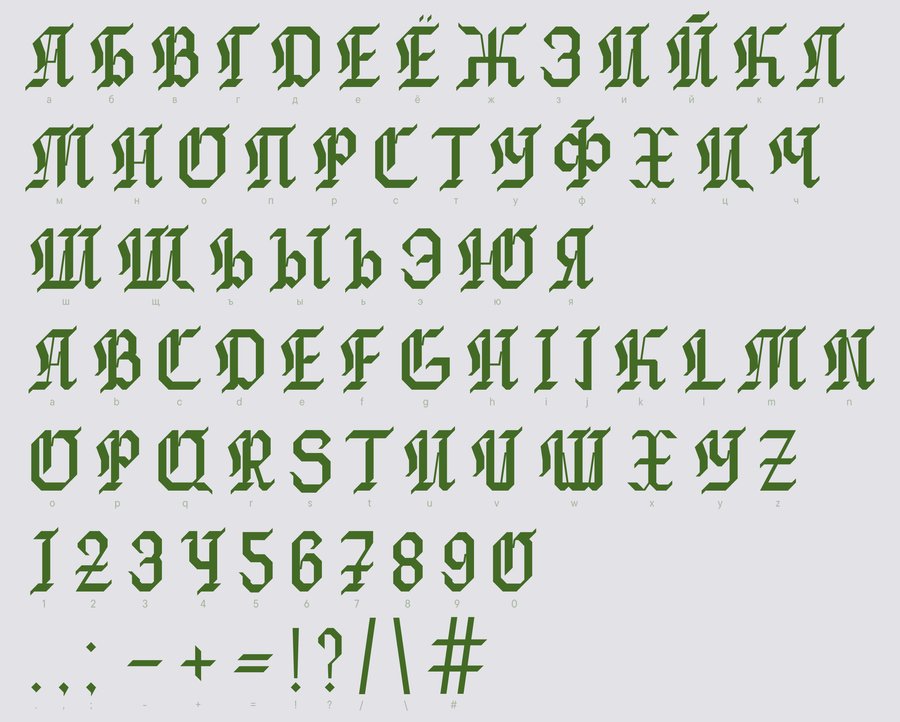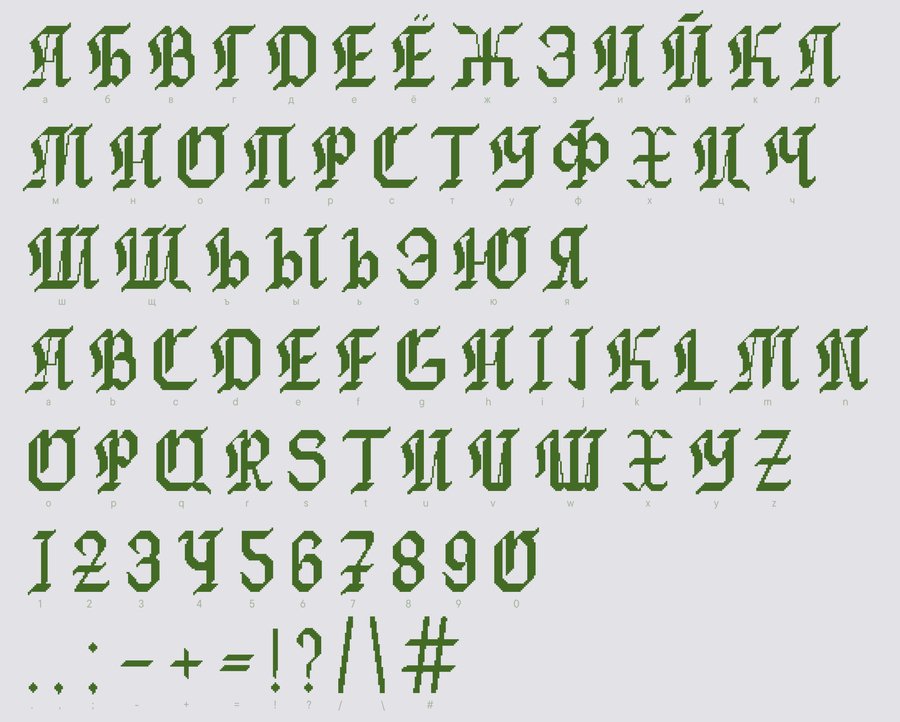
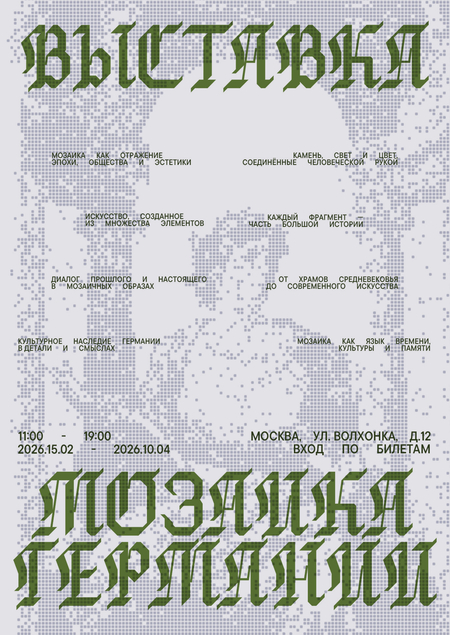
МОЗАИКА ГЕРМАНИИ
Выставка знакомит зрителей с уникальной традицией немецкой мозаики — от средневековых храмов и городских пространств до современных художественных интерпретаций.
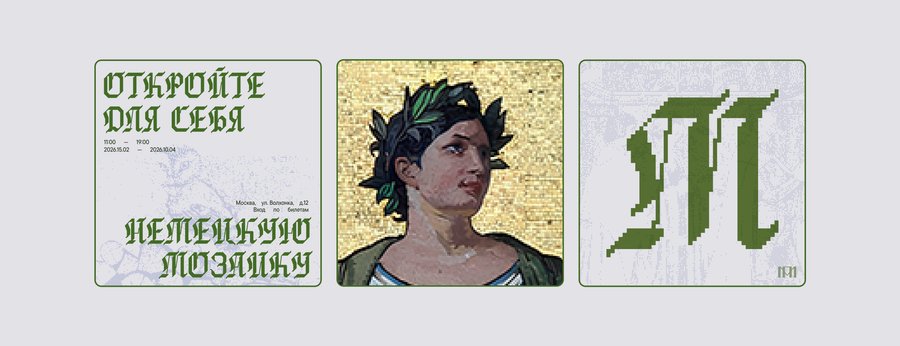
Экспонаты раскрывают, как маленькие фрагменты материала складываются в большие смыслы, отражая религию, общество, идентичность и эстетику эпох.
Специально для выставки был разработан шрифт Steinchen Typeface, отражающий идею мозаики как собранной из фрагментов истории.